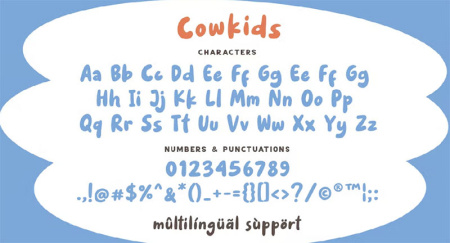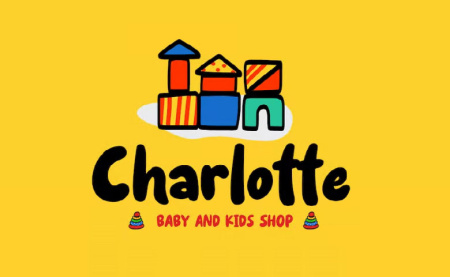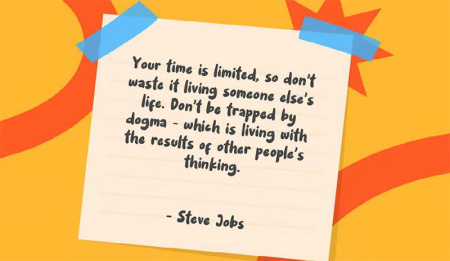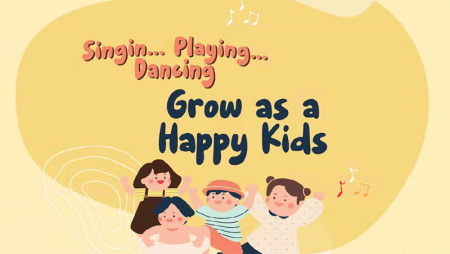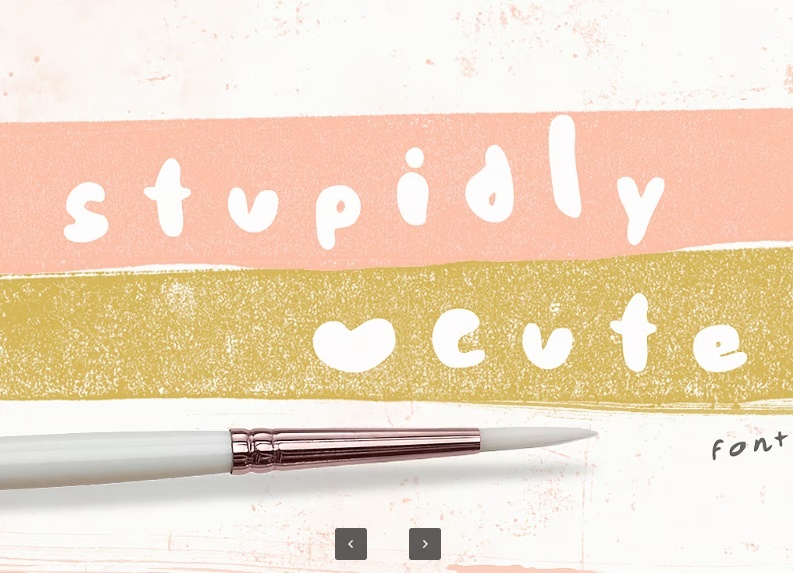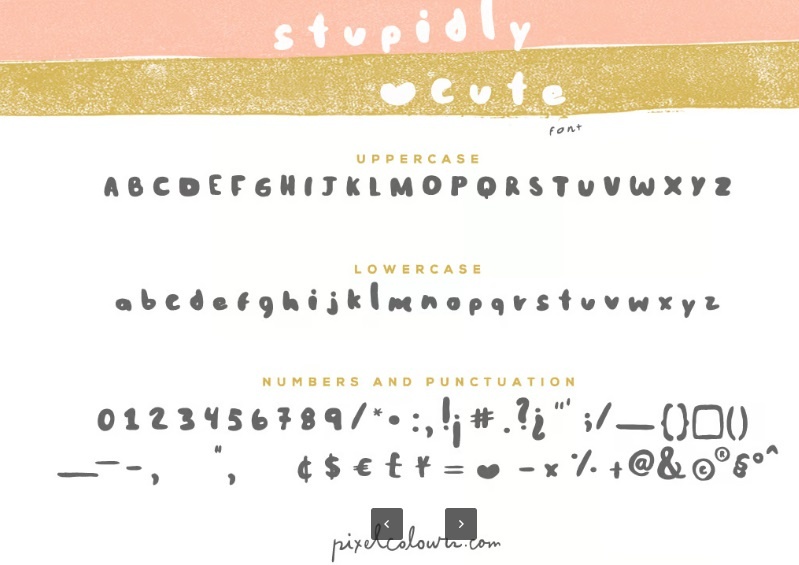
دانلود فونت بامزه انگلیسی Cowkids یک فونت زیبای دست نویس با طراحی بازیگوش و پر رنگ است. این فونت با سبک سرگرم کننده و شاد برای افزودن یک عنصر بازیگوش به کتاب های کودکان، اسباب بازی ها، بسته بندی ها یا هر پروژه ای که نیاز به حسی از شگفتی کودکانه دارد، عالی است. برای دانلود این فونت زیبا از gfxdownload.ir به ادامه مطلب مراجعه کنید.
فونت های بامزه انگلیسی می توانند به متن های شما روح ببخشند و توجه مخاطب را به خود جلب کنند. این فونتها با الهام از کارتونها و انیمیشنها طراحی شدهاند و برای طراحیهای کودکانه و سرگرمکننده بسیار مناسب هستند.
دانلود فونت بامزه و پر رنگ انگلیسی Cowkids